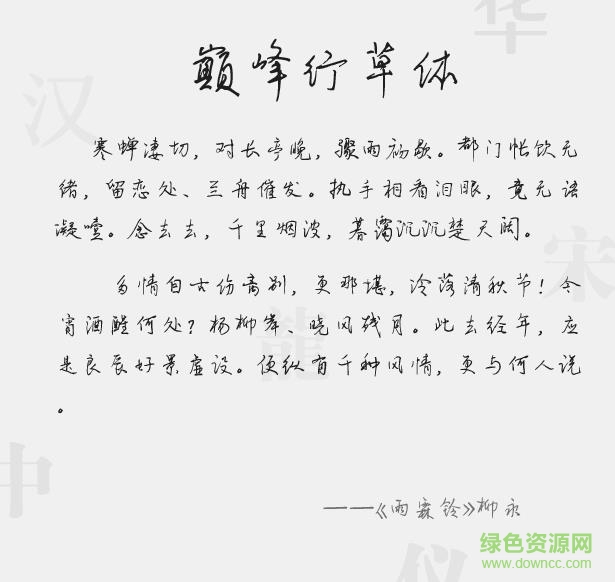
巔峰行草體
巔峰行草體能夠讓你在各類編輯中直接使用行草效果的書法字體,從而在媒體制作的時候感受到舒適的效果,在動畫作品中或者各類古代建筑都能夠十分不錯的運用!
巔峰行草體字體小編點評
這款字體在潦草中帶有十分舒適的視覺效果,讓你感覺到中華行楷的博大精深,各類獨特的字體風格都無法與它相提并論,能夠讓你使用的非常滿足
通過在使用行草將讓你獲得毛筆字體的舒適使用效果,行草中的精神以及視覺體驗擁有無可比擬的風格,給你的作品增加無窮色彩!